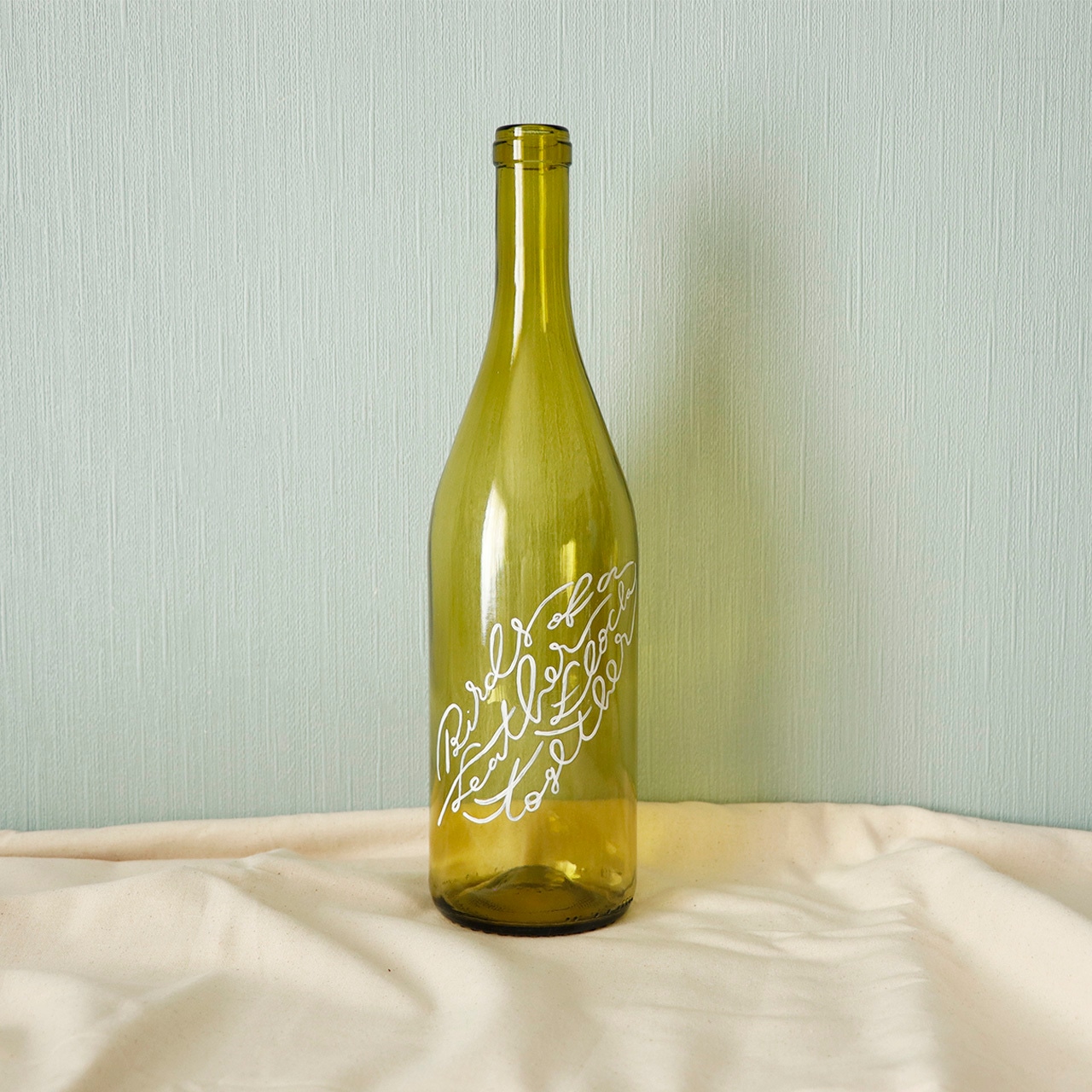
【BOTTLE PAINT ART】Birds of a feather flock together.
ワインのボトルにペイントした、気軽に飾れるアートな作品が登場!
Birds of a feather flock together.
類は友を呼ぶ
「Bird」が入っているの、鳥の羽をイメージしてみました。
光が入るとこに置くと、瓶の色とともに文字も影になって素敵ですよ!!